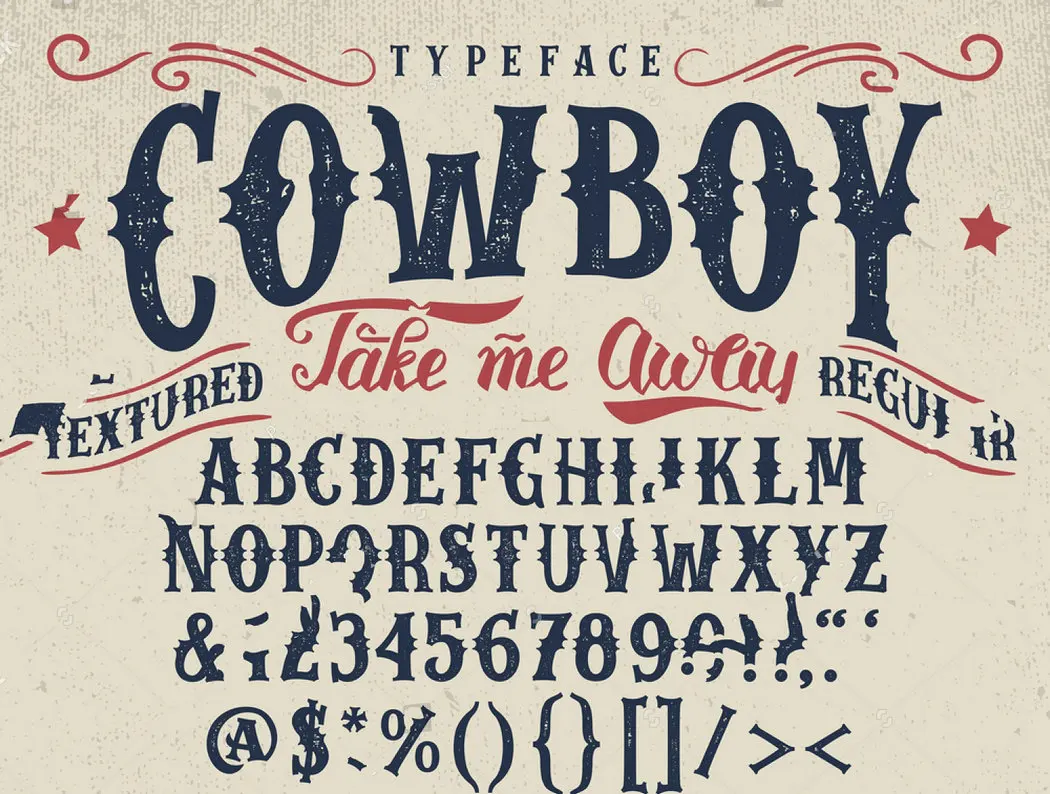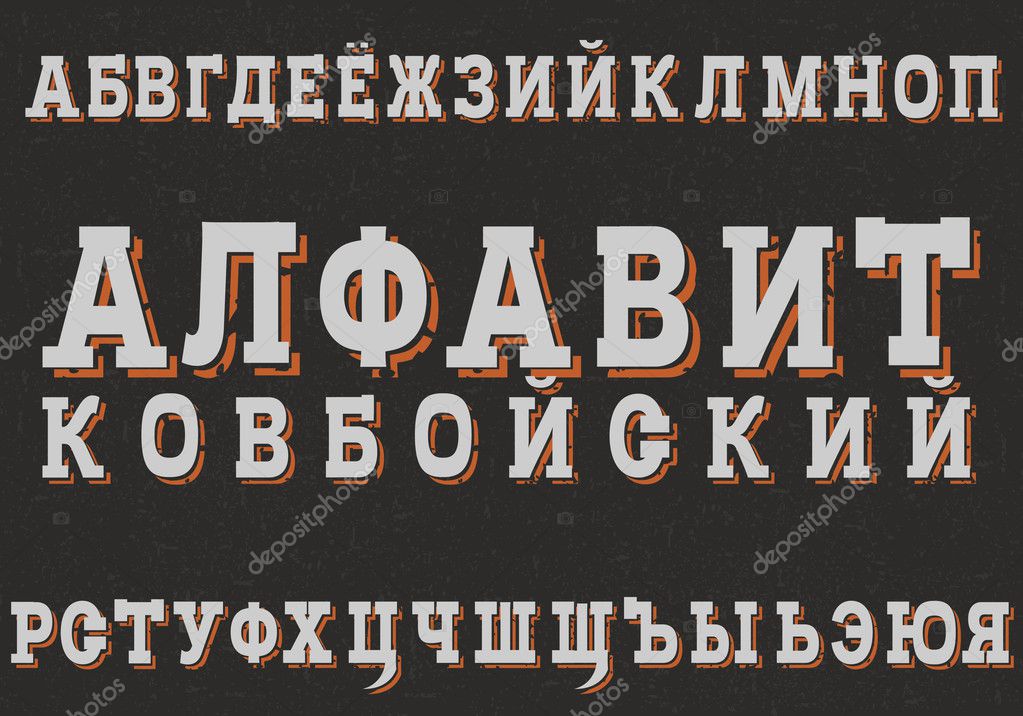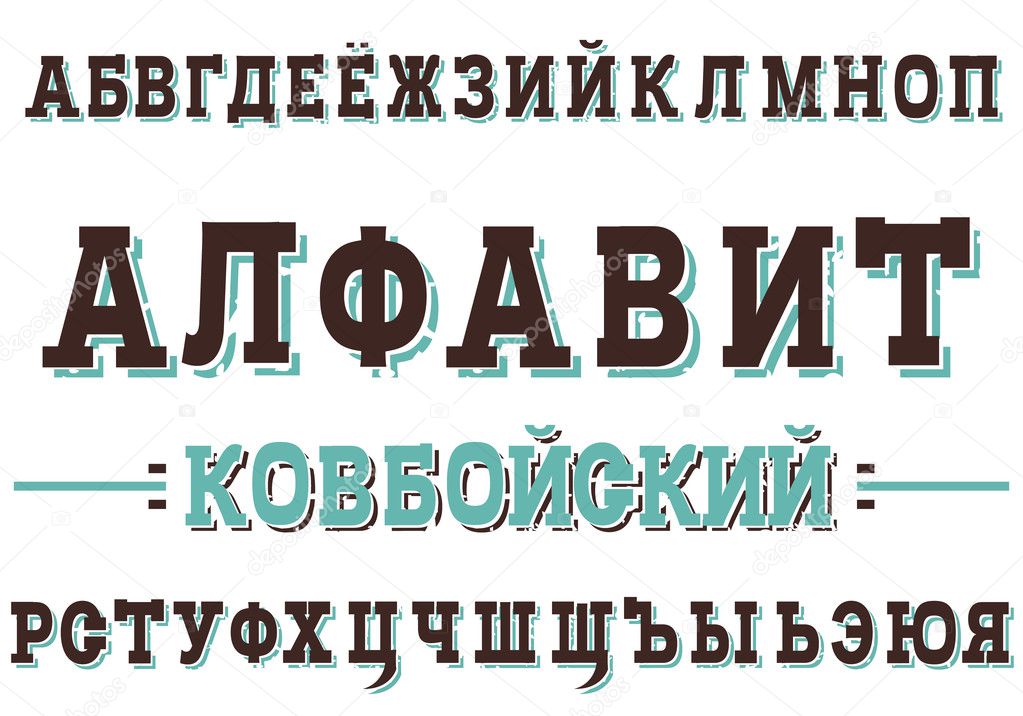
Лучшие шрифты в стиле Вестерн с поддержкой кириллицы
Вестерн или Дикий Запад – это тематика вдохновляет воображение, будоражит мысли, она нравится многим. Древняя экзотика сравни средневековым сказкам, но в другую эпоху. Соответственно, шрифты тоже используют часто для разных проектов. Очень характерные, жирные и тонкие, брусковые и с утяжелителями – их можно увидеть в веб-дизайн, печатных проектах, видеоконтенте, в оформлении обложек и многого другого.
Мы подобрали для вас лучшие и красивые шрифты в стиле вестерн, среди которых и знакомые многим по разным объявлениям и кинофильмах, и используемые в газетах того времени, при письме писем от руки и многих иных вариантах. Шрифты помогут вам оформить свои работы, сделать их ярче и запоминающимися.
FK Wild West
FK Thunderbird
Happy Sprat Cyrillic
Colt TYGRA
Cooley Ant Tuscan
Dogwood
This Night
Rio Grande
Snickers Straight
Bell flower
40+ шрифтов Best Western
Привет! Если вы графический дизайнер, вы знаете, что выбор правильного шрифта может иметь решающее значение для успеха проекта. Итак, разрабатываете ли вы веб-сайт в стиле вестерн или создаете афишу для кантри-концерта, вы будете рады узнать, что вы только что нашли золото с этой коллекцией одних из лучших западных шрифтов.
От классических шрифтов Дикого Запада, напоминающих олдскульные плакаты о розыске, до более современного взгляда на ковбойскую атмосферу — эти шрифты идеально подходят для любого проекта, требующего западного прикосновения.
The Best Western Fonts
Так что же делает западный шрифт отличным? На наш взгляд, это должно быть что-то одновременно классическое и грубое, с намеком на приключения.
Rio Grande
Это классический шрифт в стиле вестернов, который идеально подойдет для любого проекта на тему Дикого Запада, ковбоя или цирка, над которым вы работаете.
Земляничное дерево
Земляничное дерево — это шрифт с засечками, который выглядит так, как будто он вырезан из дерева. Это хорошо впишется в проект графического дизайна в стиле вестерн или ковбой.
Вестерн Бэнг Бэнг
Вестерн Бэнг Бэнг такой же крепкий и надежный, как и ковбои, которые его вдохновили. И для бесплатного шрифта у него удивительно большое количество глифов.